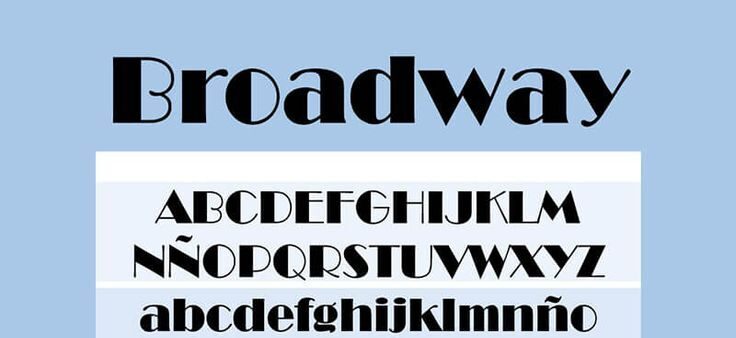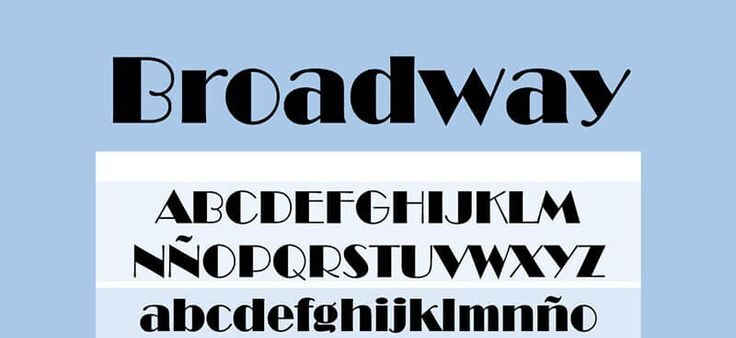
Font MTD Broadway Việt Hóa
Font MTD Broadway là một font chữ thuộc bộ font MTD mang đậm phong cách Art Deco, với các đường nét đậm, góc cạnh và mạnh mẽ, gợi nhớ đến sự hào nhoáng của những tấm biển quảng cáo từ thời kỳ hoàng kim của sân khấu Broadway. Bộ font này thường được sử dụng trong các thiết kế cần sự nổi bật và sang trọng, như poster, tiêu đề, logo, hoặc các ấn phẩm quảng cáo. Font MTD Broadway giúp tạo nên ấn tượng mạnh mẽ và tinh tế, lý tưởng cho các dự án mang phong cách cổ điển nhưng vẫn hiện đại, thu hút người xem ngay từ cái nhìn đầu tiên.